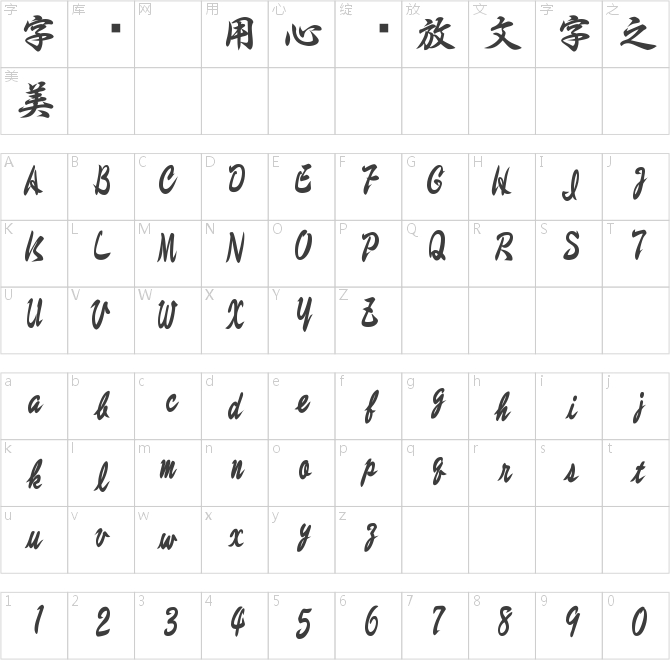
方正任利生字體 詳情頁
字體名稱: 方正任利生字體
方正任利生字體
方正任利生字體介紹
方正任利生字體字體字庫是一款讓人賞心悅目、百看不厭的中文字體,適合各類廣告和產(chǎn)品包裝設(shè)計應(yīng)用,字體大小2.48MB,格式為ttf字體,上傳用戶是星期一,作者/版權(quán)方為方正字庫